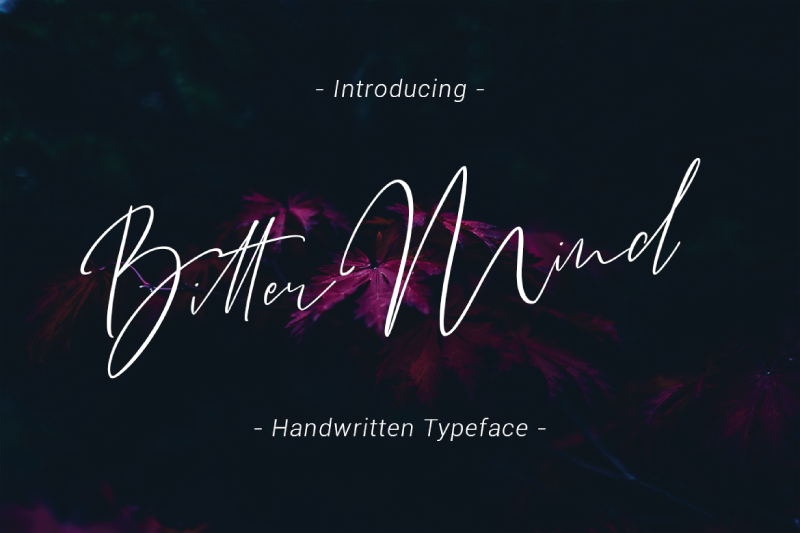
Bitter Mind Script Font – Download Grátis
Este é um belo estilo de fonte escrita à mão, ideal para projetos modernos que exigem uma aparência sofisticada e formal. Introduzimos a fonte Bitter Mind. Ela foi especialmente projetada para trabalhos gráficos como casamentos, capas de livros, cartões de convite, logotipos, marcações, cartões de visita e certificados — em resumo, qualquer tipo de projeto que necessite de um olhar clássico, formal ou luxuoso. Ideal para quem busca dar vida a seus projetos com uma aparição elegante e criativa. Aproveite essa fonte única e moderna para dar o tom perfeito ao seu próximo trabalho.